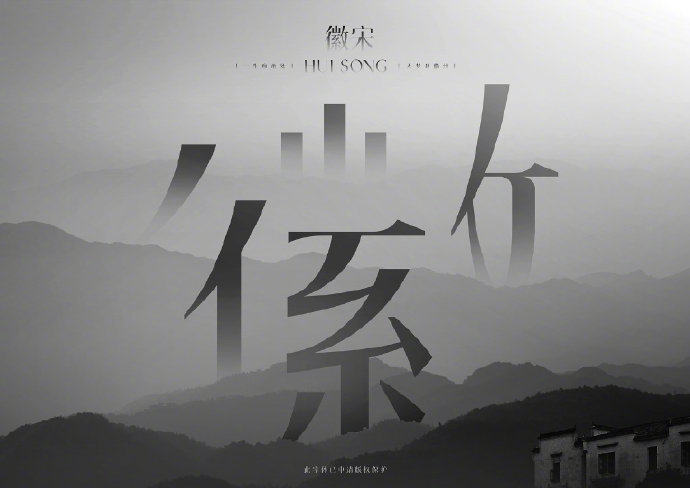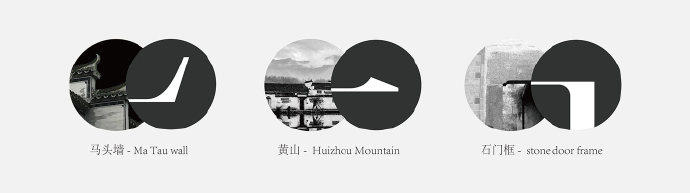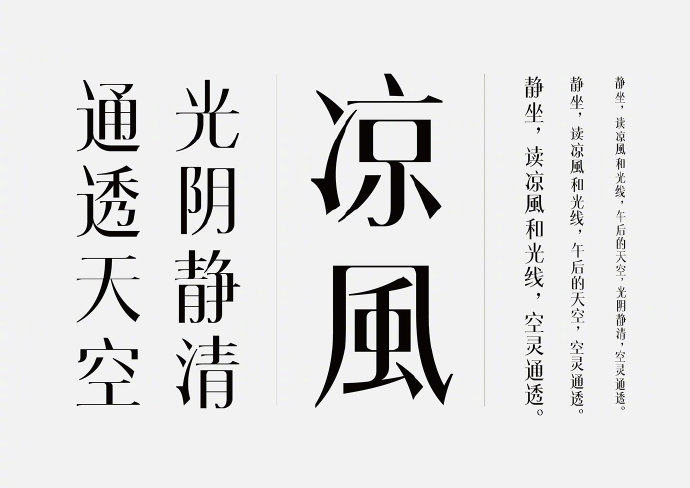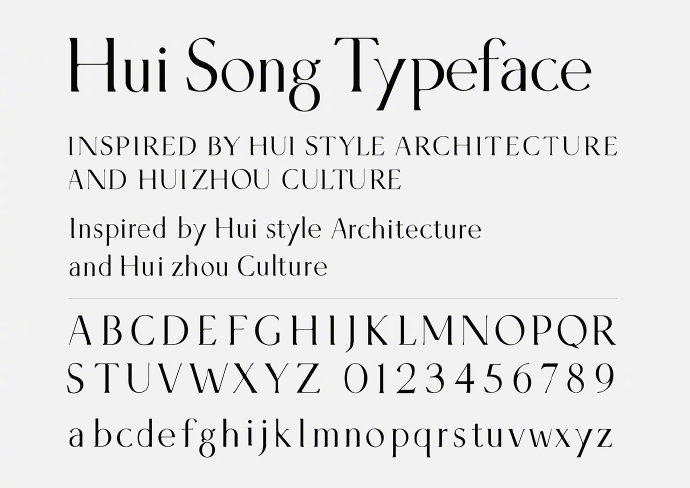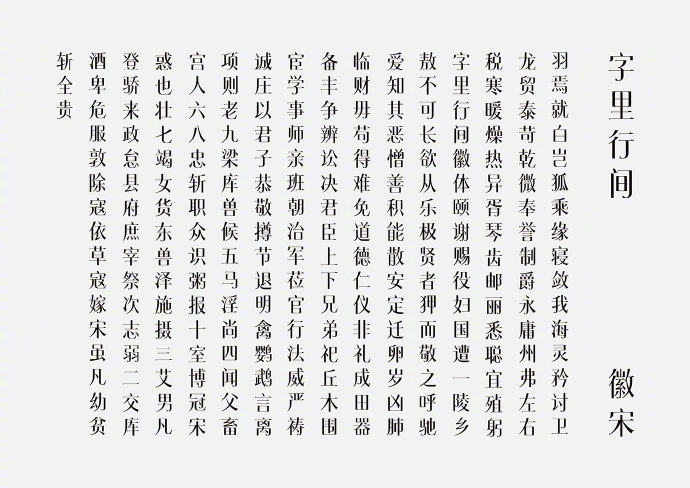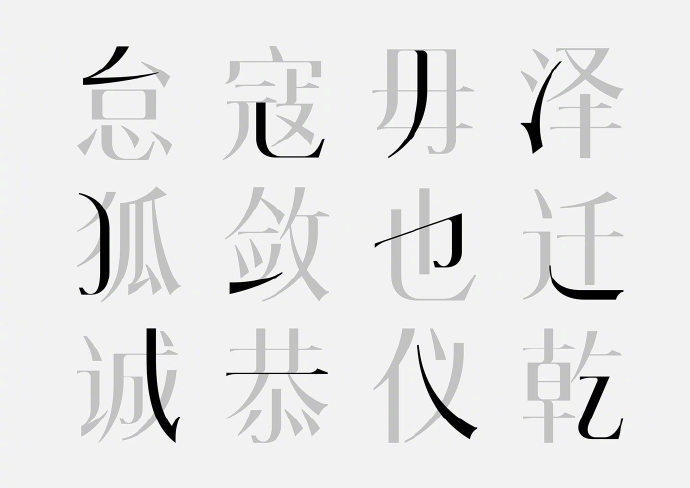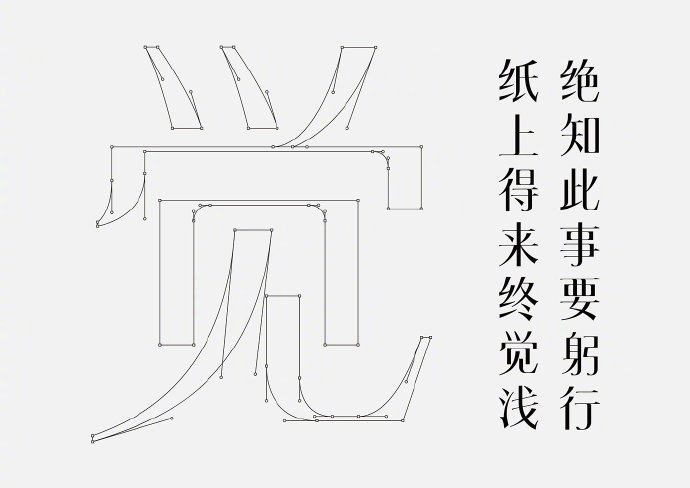
项海龙徽宋体-Huisong | 基于宋体融合“徽州”文化元素设计而出的创意字体
近日,@项海龙Gracebrand 发布了一款新字体:徽宋-Huisong。
徽宋是一款在“宋体”字基础上汲取“徽州”文化元素设计而出的一款创意字体。“徽州”在明清之际富甲一方,虽然养在深山之中,却形成独树一帜的“徽州文化”,其中徽派建筑最具代表。项海龙出生于徽州成长于徽州,对于家乡文化的热爱是这款字体诞生的起源。
徽文化的视觉符号中,马头墙和翘角最具代表的元素,因此在字体设计中“直角”和“扬翘”的形融入到此款字体的部分笔画中,使之成为字体的独有风格。 徽宋体从传统文化中来,运用现代设计语言的表现,整个字体“刚柔并济”,令人印象深刻。
徽宋体-Huisong
徽宋体
徽宋体-Huisong
Huisong